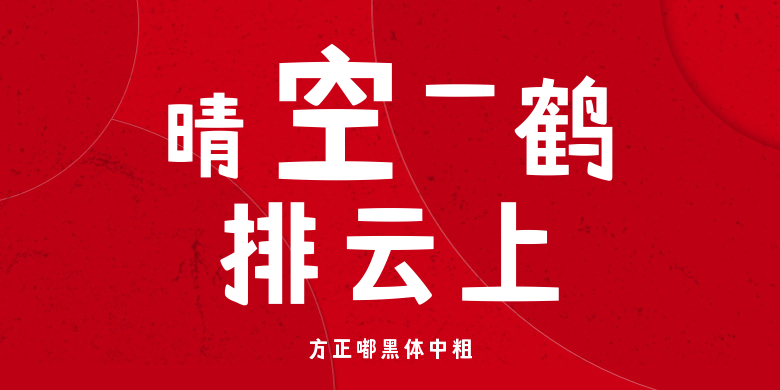
方正嘟黑体中粗
方正嘟黑体中粗,这款字体结构工整、笔画清晰,兼顾美观与易读性,适用于标题、正文、海报、包装、LOGO 等多种场景。字形优雅稳定,风格百搭耐看,适配日常排版与创意设计,让文字呈现更舒适、更具质感。方正嘟黑体中粗一笔一画,皆是细节,以均衡的比例、流畅的线条打造舒适视觉体验,字形端正大气,风格简约现代。无论是商业设计、品牌宣传还是日常排版,都能轻松驾驭,让文字更有格调与力量。方正嘟黑体中粗字体下载。